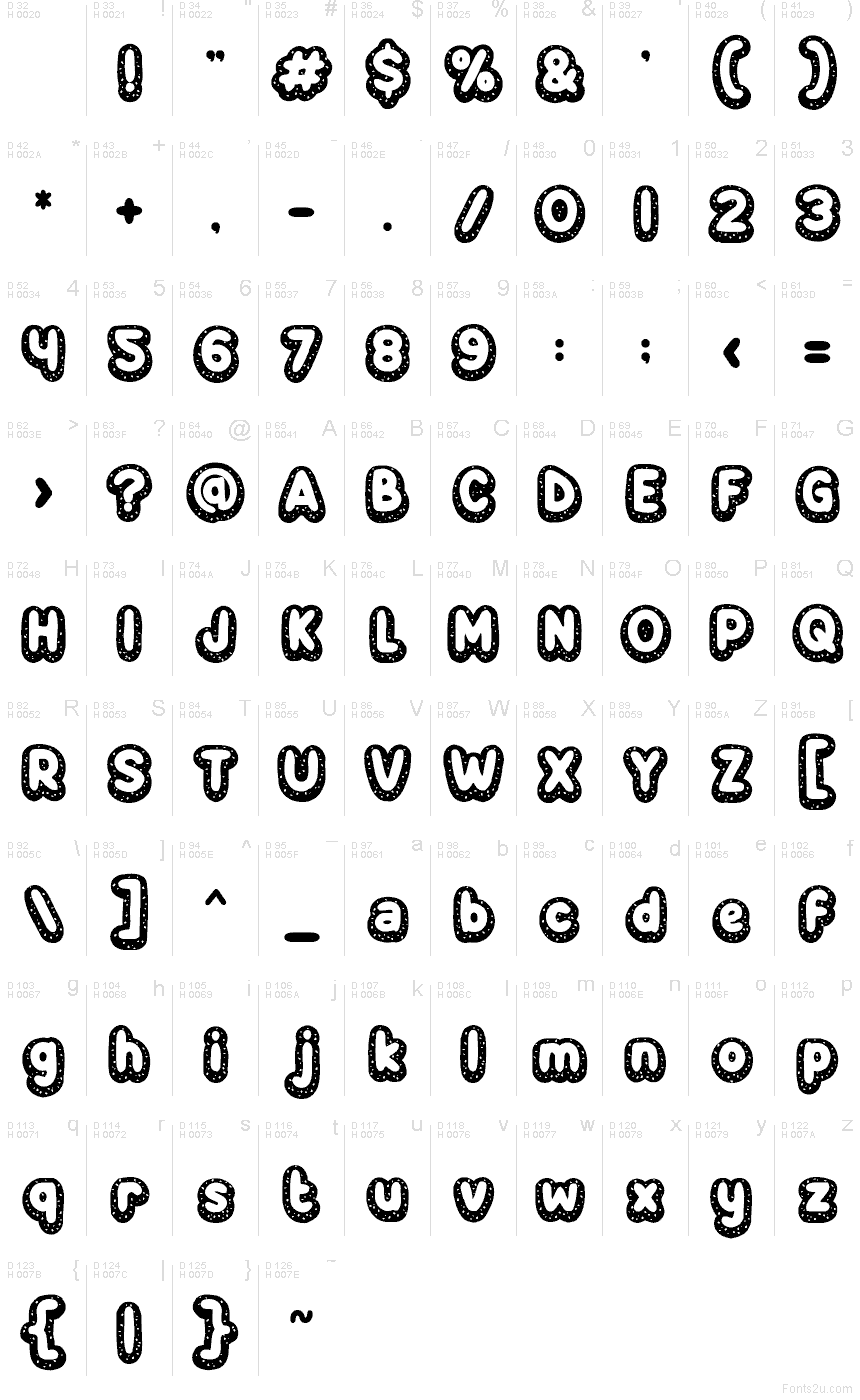
Cake Couture One
Cake Couture One von Putracetol Studio ist eine verspielte Bubble-Display-Schrift im Candy-Shop-Look mit einer charmanten Glasur-Optik. Die Buchstaben sind rund und voluminös, durchzogen von kleinen Punkten, die wie Zuckerstreusel wirken. Dadurch erinnert das gesamte Alphabet eher an frisch dekorierte Kekse oder Tortenbeschriftungen als an eine einfache dekorative Schriftart.
Durch diese zuckrige Textur eignet sie sich perfekt für Bäckerei-Branding, Geburtstagseinladungen, Verpackungsdesign für Kinderprodukte, Party-Poster und Dessert-Menüs. Als kostenloses Font ist es ideal für kurzweilige Social-Media-Grafiken, Cover-Texte und Titelkarten, bei denen die weichen Formen und Konfetti-artigen Sprenkel das Design tragen, ohne dass es viel mehr braucht.